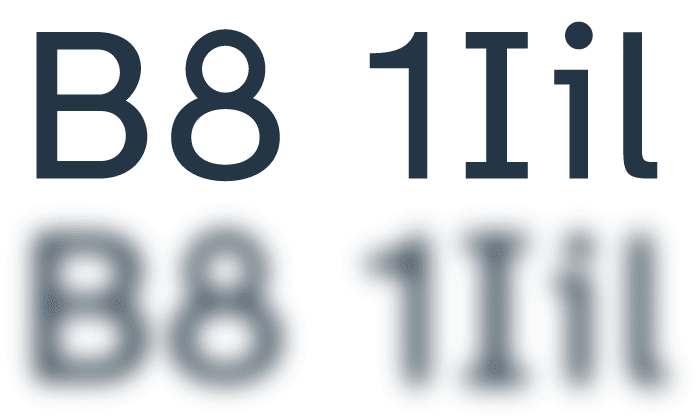
Interrobang #1 – Pares, legibilidade e mulheres na tipografia
Respondendo perguntas de escritores
Hoje eu inauguro o Interrobang, uma nova linha do Tipo Aquilo voltada a responder dúvidas e perguntas de leitores e pessoas curiosas a respeito de design e tipografia. Mais ou menos como na edição #38, só que um pouco mais sério, com menos perguntas e respostas mais completas.
Cadu, lembro de produzir um livro e queríamos encontrar fontes produzidas por mulheres e, na época, tinham pouquíssimas. Isso melhorou? (Ana Rüsche, do Anacronista e Incêndio na Escrivaninha)
Antes de tudo: as mulheres sempre estiveram presentes na tipografia fazendo todo tipo de trabalho na indústria, da criação de fontes à composição de tipos e produção de impressos. Feita essa observação, a oferta de fontes feitas por type designers mulheres aumentou bastante na última década, e a presença delas em foundries de todos os tamanhos também cresceu. Iniciativas como o Alphabettes e o The Malee Scholarship vem abrindo espaço para que mais mulheres, trans e não-binários estabeleçam-se na indústria e façam ela ser mais igualitária. Embora o mercado global de design aponte uma presença quase igualitária entre homens e mulheres, o setor tipográfico ainda não vive essa paridade.
Algumas reflexões da Deia Kulpas e da Flavia Zimbardi sobre esse tema são válidos, mas também trazem otimismo. Uma produção tipográfica mais igualitária não depende apenas de mais mulheres fazendo fontes, mas também que elas estejam nos júris de premiações, na liderança executiva de foundries, na formação de novos designers de tipos, e em palestras e conferências. Aos poucos, esses espaços estão sendo preenchidos, a exemplo do DiaTipo, que desde 2018 compromete-se a um line-up de palestrantes pelo menos 50% feminino.
E vejam que interessante: uma pesquisa de 2020 do serviço Rentafont, por exemplo, mostra que apenas 4% do acervo de fontes feitas por mulheres parecem “femininas”, enquanto 80,7% são vistas como “unissex”. Esse tipo de informação ajuda a derrubar o preconceito de que type designers mulheres fazem fontes “femininas”, só que a noção que muitas pessoas ainda têm de gênero em fontes precisa ser quebrada. A ideia de que algumas formas de letras são mais “masculinas” ou mais “femininas” que outras não é nada menos que sexismo mesmo.
Cadu, qual a sua opinião sobre a fonte Atkinson Hyperlegible? Cumpre o que promete sobre ter “grande legibilidade e leiturabilidade para pessoas com visão baixa”? (Rodrigo Pontes, autor de “As Neurofiandeiras do Val”)
Eu vou deixar a resposta um pouco mais abrangente, porque legibilidade e leiturabilidade merecem explicações melhores. Legibilidade envolve questões que independem das formas das letras de uma fonte. Por exemplo, tem pessoas que arrepiam só de pensar em um livro inteiro composto com fonte sem serifa, e provavelmente terão um ritmo de leitura mais devagar por estranhamento e falta de costume. Outra questão sobre legibilidade tem a ver com contexto, pois nós temos ritmos de leitura diferentes de acordo com o contexto em que estamos lendo, como a leitura de rastreio que nós comumente fazemos na Internet, e a leitura linear que fazemos com livros, revistas e jornais.
Mesmo essa leitura linear não é tão linear assim: conforme a pessoa se alfabetiza, ela deixa de ler letra-por-letra, e a leitura passa a funcionar por reconhecimento de formas e padrões de palavras mais comuns. Grosso modo, é como se a gente visse uma mancha com uma forma específica e o cérebro busca qual palavra preenche melhor essa mancha. Por sua vez, a leiturabilidade é um conceito em que nós designers somos treinados a melhorar no aspecto visual, mas ficamos impotentes nos aspectos relacionados ao conteúdo do texto: não há diagramação possível que torne mais agradável de ler um texto mal-escrito e feito para um público diferente.
Dito tudo isso, eu acho complicado uma fonte prometer tanto sobre "oferecer maior legibilidade”. A Atkinson Hyperlegible propõe soluções interessantes que concernem apenas uma parte do problema. São legais as propostas de resolver ambiguidades em letras comuns, embora o uso de alturas iguais de minúsculas com ascendentes e maiúsculas seja uma oportunidade perdida de oferecer uma clareza ainda maior. Não existe uma forma de uma fonte só resolver todos os problemas de legibilidade, tanto de contexto quanto de deficiências visuais ou de transtornos de leitura e aprendizado.
Existe alguma ferramenta de pareamento de fontes, como existia no Google Fonts, em que eu escolho uma fonte principal e ela sugere opções para combinar? (Claudia Dedeski, do Newsletter da Gambiarra)
A que eu acho mais simples de usar com o acervo do Google Fonts é o FontJoy, que cria pares de fontes e permite visualizar a combinação. Tem também o pareador da Monotype, mas o acervo dela é de fontes com licença comercial. Uma tendência, protagonizada pelo próprio FontJoy, é o uso de inteligência artificial e aprendizado de máquina para oferecer combinações de fontes melhores, de acordo com o contexto.
No entanto, além dessas ferramentas, é importante ver o que outros designers produzem e como eles combinam fontes com atributos que parecem difíceis de combinar. Tem outros sites legais que reúnem exemplos usados, como o Typ.io e o meu favorito da vida, o Fonts In Use. O artigo da Bethany Heck sobre o valor de um design com múltiplas tipografias (traduzido em português pelo Valter Costa, da Plau) é muito valioso pra quem quer trazer mais sabor para os seus trabalhos combinando três, quatro ou mais fontes sem que ele vire apenas uma maçaroca.